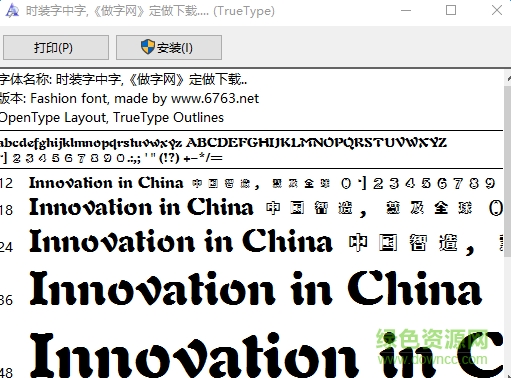
時裝字中字
時裝字中字是時裝字庫中的一款藝術(shù)字體,這款字體寫出來的字是很好看的,而且實用性強,可以用于很多方面,當(dāng)然如果大家喜歡這款字體,不管是用在什么方面都是可以的,歡迎大家來綠色資源網(wǎng)下載。
時裝字中字字體是一款很有用的電腦字體,用于書本印刷、廣告設(shè)計等方面再合適不過了,大家喜歡的話可以來綠色資源網(wǎng)下載。